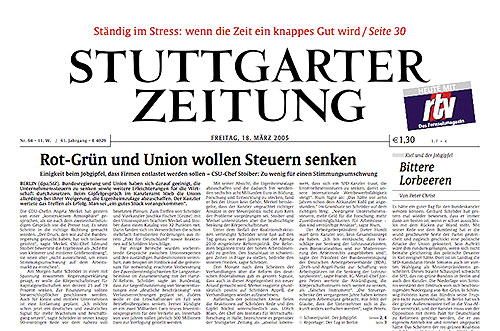
FontShop entwickelte Stuttgarter-Zeitung-TitelschriftDie Stuttgarter Zeitung ist zu Recht stolz auf ihren
unverwechselbaren, gezeichneten Schriftzug im Titelkopf. Lokalausgaben (zum
Beispiel die Leonberger Kreiszeitung) sollen nun in der gleichen
Titelschrift erscheinen. Ein Fall für Corporate Font von FontShop,
wo ein komplettes Alphabet aus dem Schriftzug »Stuttgarter Zeitung«
entworfen wurde. Weiterlesen ...